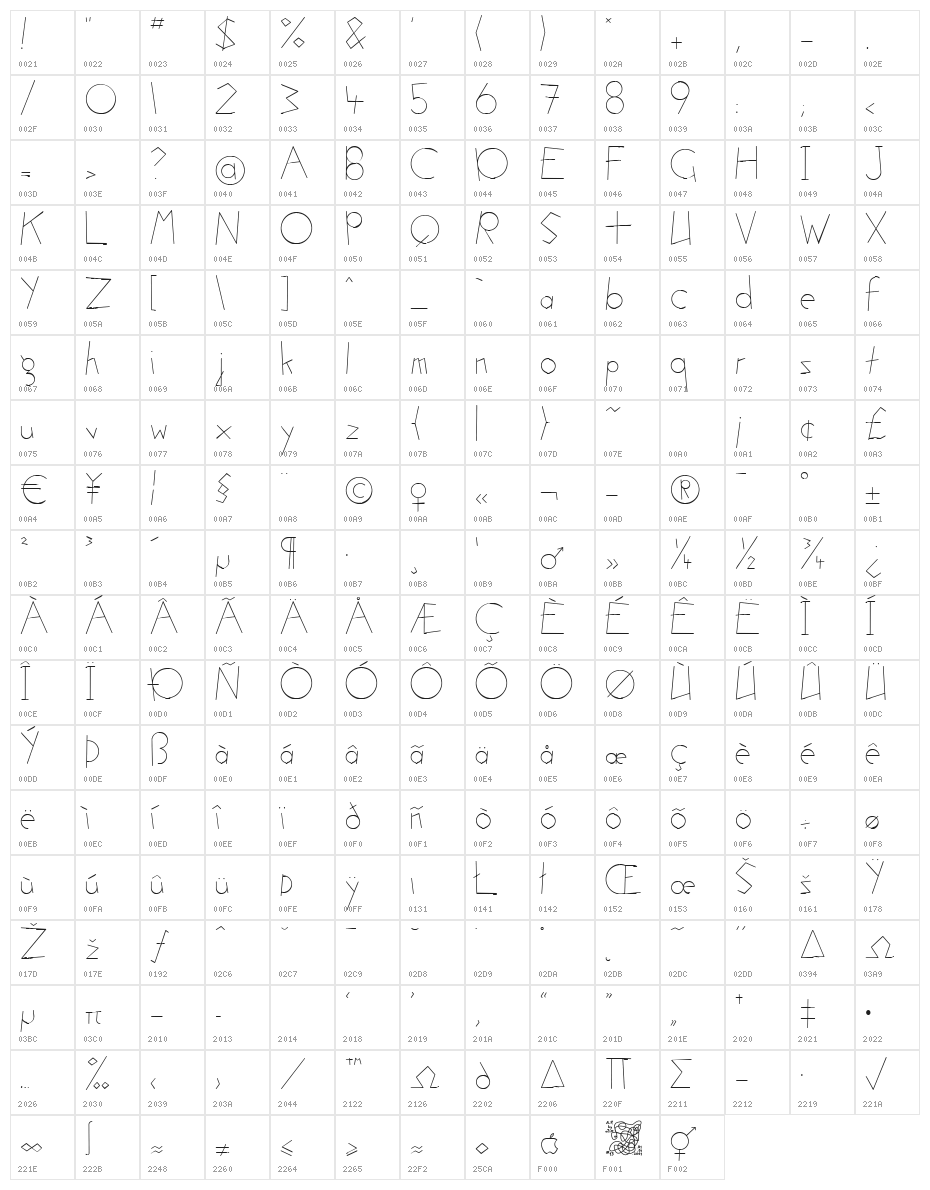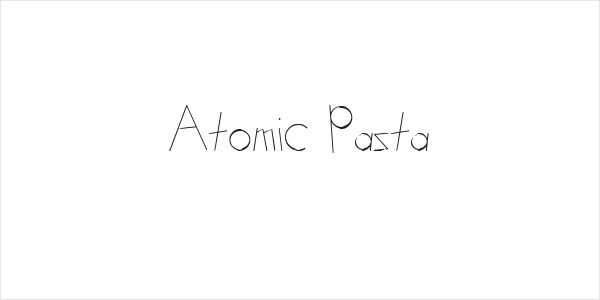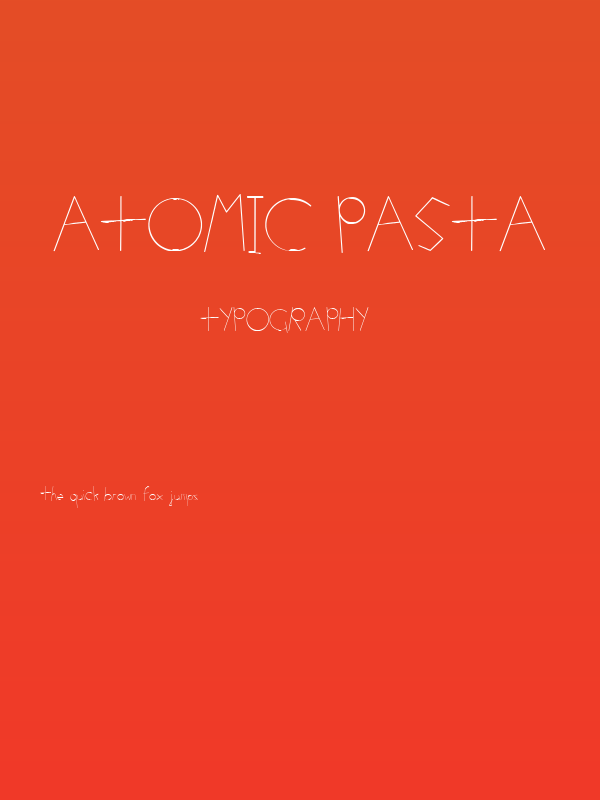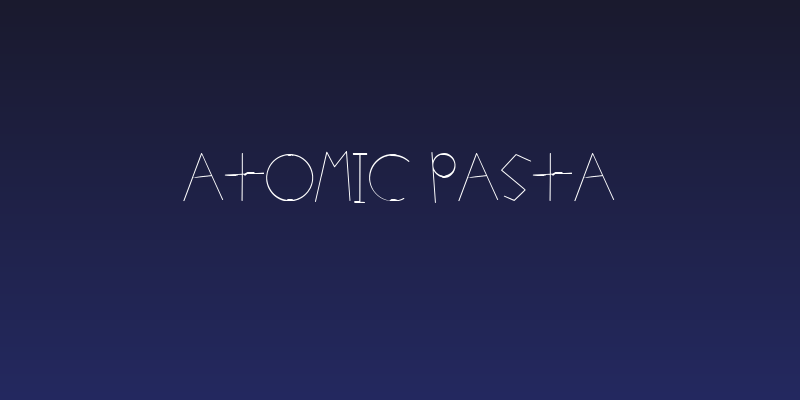
Atomic Pasta Font
| Caso d'uso | Logos, Posters, Invitations |
| Progetti proposti | Ideal for children's books, creative posters, playful branding, and artistic invitations. |